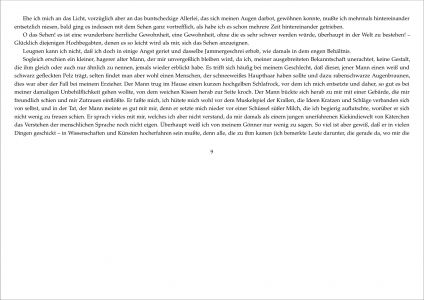
Die optimale Zeilenlänge von Texten
Ich sprach vor kurzem mit einem Professor von mir über die Lesbarkeit von Texten. Er ist der Meinung, dass Texte besser lesbar wären wenn man A4-Seiten im Querformat und nicht im Hochformat verwenden würde. Sein Argument dafür lautet, dass bei einem Menschen die Augen nebeneinander angeordnet sind und der Mensch desshalb eher horizontal als vertikal sieht. Ich bin jedoch der Meinung, dass man A4-Seiten nicht umsonst im Hochformat verwendet.
Ich habe hier, aber auch auf anderen Internetseiten gelesen, dass die optimale Zeilenlänge zirka 70 Zeichen beträgt. Diese Zahl spricht ganz klar für ein Hochformat bei einer A4-Seite. Meine Frage lautet nun, gibt es fundierte Studien, die das belegen und auch Gründe dafür nennen? Ich würde mich freuen wenn ihr mir ein paar Links zu solchen Studien posten könntet.
Was Dein Herr Professor gesagt ist, ist gelinde gesagt Unsinn. Denn wenn Du wirklich eine Zeile über die ganze Breite von 297mm bringen würdest, bräuchtest Du einen gigantischen Zeilenabstand, damit das Auge den Anfang der nächsten Zeile finden kann.
Außerdem hast Du das Problem der Doppelseiten. Es gibt Studien (allerdings habe ich gerade keine Quelle parat), die besagen, daß das männliche Auge eine Doppelseite im A4-Querformat bei realistischen Betrachtungsabstand nicht auf einen Blick erfassen kann. (Der Blickwinkel von Frauen ist etwas größer.)
Ich hoffe, der Professor hat nichts mit Gestaltung am Hut …
(wahrscheinlich Informatik-Prof. oder BWL?) :wink:
Ich würde ihm zur Strafe einfach mal eine Hausarbeit im Querformat abgeben. Sicher hat er nichts dagegen, wenn die Seitenränder rechts, links und oben nur 1cm sind, er kann dann ja unten seinen Kommentar dranschreiben, schließlich sind die Hände ja auch unter den Augen!
Hausarbeit im CinemaScope-Format -- da passen locker 250 Zeichen in eine Zeile, wenn man dafür nur 10 Zeilen nimmt hat man denselben Inhalt untergebracht (vorausgesetzt, man macht nur wenige Absätze).
::]Ich hoffe, der Professor hat nichts mit Gestaltung am Hut …
(wahrscheinlich Informatik-Prof. oder BWL?) :wink:
Bei meinem Studiengang ist er für Geschäftsprozesse im Bereich e-business zuständig. Früher hat er beim öffentlich-rechtlichen Fernsehen in Österreich gearbeitet. Später dann als Leiter von österreichischen Printmedien.
Er sagte auch, dass die beim Fernsehen begriffen haben wie das Blickfeld eines Menschen aussieht und desshalb hat der Fernseher heute ein Format von 4:3 oder bei neuen Fernsehern sogar 16:9.
Bei Printmedien werde nur desshalb so kurze Zeilen verwendet weil es zur Zeit als die ersten Bücher entstanden sind noch kein Eye-Tracking oder der gleichen gab. Ausserdem konnte man früher nur sehr schmalle Druckplatten herstellen. Heute hat man sich einfach an dieses Format gewöhnt und desshalb möchte man nicht davon abkommen.
Dann wird er auch eventuell vorgelegte Studien als veraltet abtun.
Das einzige was du machen kannst ist demonstrieren dass Querformat (eigentlich zu lange Zeilen) schlechter funktioniert als andersrum.
Was er behauptet mag ja für das Blickfeld stimmen, aber lese ich wirklich mit dem gesamten Blickfeld? Dann würde ich auch die Augen beim Lesen nicht bewegen, ich kann die Seite ja auch so überschauen.
Dann wird er auch eventuell vorgelegte Studien als veraltet abtun.
Das einzige was du machen kannst ist demonstrieren dass Querformat (eigentlich zu lange Zeilen) schlechter funktioniert als andersrum.
Was er behauptet mag ja für das Blickfeld stimmen, aber lese ich wirklich mit dem gesamten Blickfeld? Dann würde ich auch die Augen beim Lesen nicht bewegen, ich kann die Seite ja auch so überschauen.
Genau das ist auch meine Meinung. Bei einem Bild kann ich das komplette Bild auf einmal betrachten ohne die Augen bewegen zu müssen. Bei einem Text muss mich auf eine Stelle konzentrieren um die Schrift scharf zu sehen und dann mit diesem kleinen Bereich indem ich scharf sehen kann von Wort zu Wort wandern.
Übrigens soll ich für die nächste Vorlesung eine Präsentation erstellen in der ich meine Meinung untermauere. Ich werde in der Präsentation Bilder, Videos und Texte zeigen damit alle den Unterschied beim Sehverhalten erkennen können.
Ich habe grade mal eine Horrorversion des Kater Murr erstellt. Ein schöner Text mit schöner Schrift, mit Randausgleich und großzügigem Durchschuss, 420 Seiten mit 180 Zeichen pro Zeile. Leider reicht mein Webspace zur Zeit fürs pdf (1,2MB) nicht aus, kann ich aber gern mailen.
Gruß, Georg
PS: Hier mal eine Seite – leider in eingeschränkter Qualität, da das Forum kein pdf nimmt:
PPS: Sehe grade, dass das Beispiel in letter-Format gesetzt ist, aber das dürfte im Grunde nicht viel ändern. Wird in A4 eher noch schlimmer.
Die Thesen der Lesbarkeitsforschung zusammenzufassen, ist mir im Moment zu mühsam. Deshalb einfach ein bisschen gesunder Menschenverstand: Technisch machbar wäre Quer statt Hoch bzw. breite Kolumnen ja seit jeher gewesen – tatsächlich jedoch verwendet die überwältigende Mehrheit der ‹westlichen› Texte der letzten sechs Jahrhunderte keine solchen Formate. Es kann ja kaum sein, dass sich die gesamte Menschheitsgeschichte bis zu Deinem Professor geirrt haben sollte?